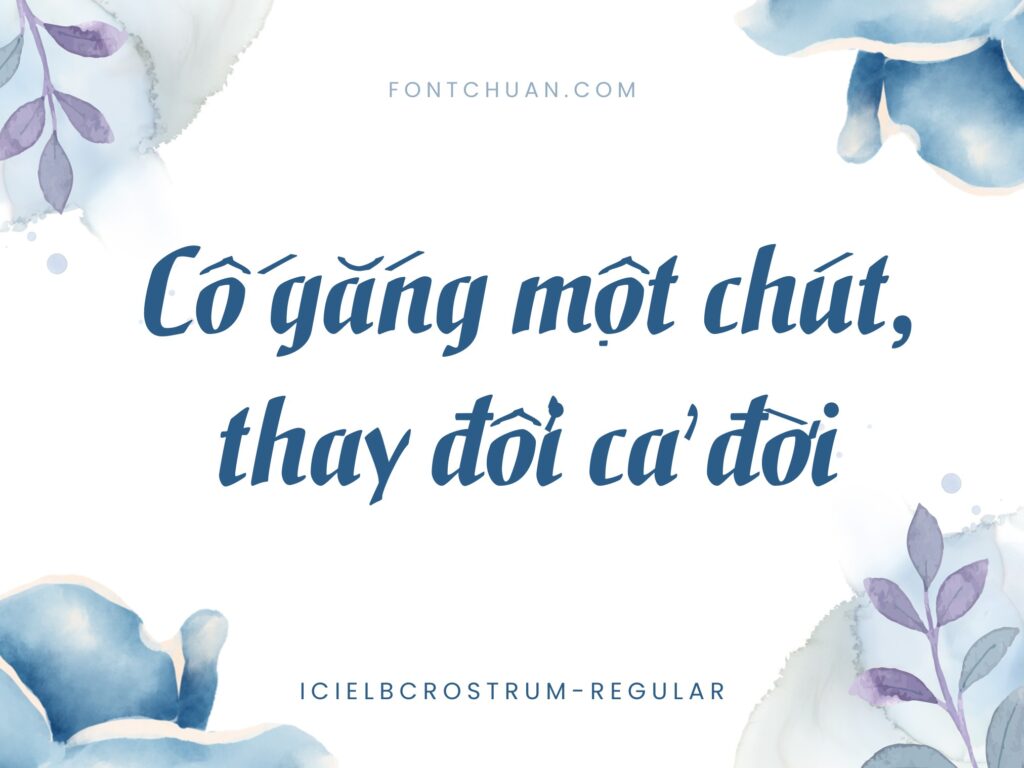
Font iCiel Bc Rostrum Regular Việt Hóa
Tác giả Font: Canada Type Design, Julius Kirn, ...
Việt hóa bởi: Iciel
BC Rostrum Regular là một font chữ sans-serif mang phong cách cổ điển, được thiết kế bởi Julius Kirn vào năm 1938 cho xưởng đúc Genzsch & Heyse ở Hamburg. Font này nổi bật với các ký tự in hoa và đường nét đậm, tạo sự thu hút mạnh mẽ trong các thiết kế. Để hỗ trợ cộng đồng thiết kế Việt Nam, Iciel đã Việt hóa font BC Rostrum Regular, giúp font này hỗ trợ đầy đủ tiếng Việt cùng hơn 200 ngôn ngữ khác. Phiên bản BC Rostrum Regular Việt hóa đã được thành viên Font Chuẩn sưu tầm và đăng tải, mang đến sự lựa chọn đa dạng cho các nhà thiết kế.
Về đặc điểm thiết kế, BC Rostrum Regular sở hữu các ký tự in hoa với nét chữ đậm và góc cạnh, tạo nên sự cân đối giữa tính mạnh mẽ và sự cổ điển. Font này rất phù hợp cho các thiết kế như tiêu đề, poster, logo, bao bì sản phẩm và các dự án cần sự nổi bật. Ngoài ra, BC Rostrum Regular cũng là lựa chọn lý tưởng cho các ngành nghề như quảng cáo, bất động sản, giáo dục và công nghệ, mang lại phong cách chuyên nghiệp và hiện đại. Font này cũng thích hợp để sử dụng trong các sự kiện như lễ hội, sinh nhật và các dịp đặc biệt khác.